Powyższy obraz to fragment strony www.gmina.pl. zamieszczony tu w celach ilustracyjnych. (c) Szulc Efekt Sp. z o.o. (Font użyty w nawigacji ww. strony to właśnie FF DIN Regular.) Sprawa ew. bezumownego użycia fontu FF DIN w szablonach stron WWW Urzędów Gmin
Trochę faktów dla dociekliwych...
Przy tworzeniu stron WWW (tak jak przy projektowaniu publikacji) możemy zastosować różnego rodzaju liternictwo - czcionki (fonty).
Font FF DIN jest prawdopodobnie bezumownie używany również przez samą firmę Szulc Efekt Sp. z o.o. na stronie www.gmina.pl
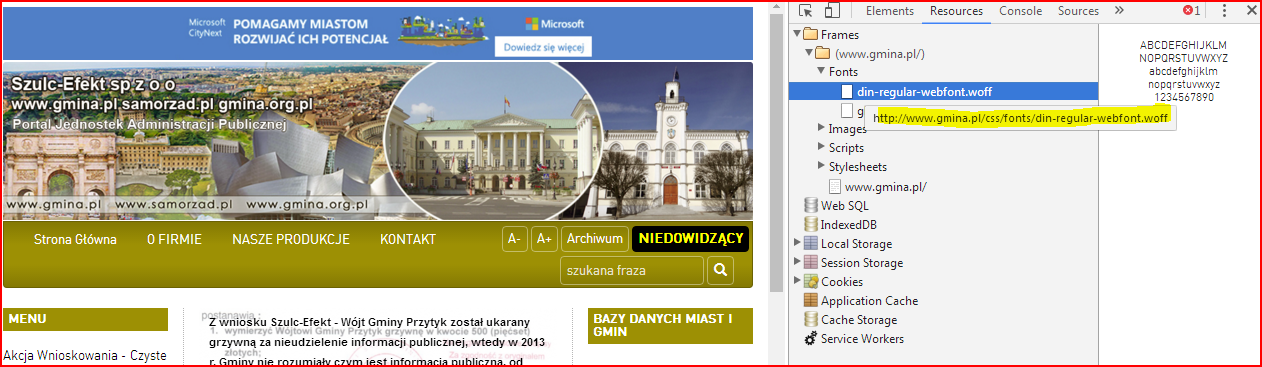
a dokładnie widać, że mówimy tu o:
Font FF DIN jest fontem bardzo czytelnym w małych wielkościach (w małych stopniach pisma) i dlatego jest fontem popularnym w zastosowaniach internetowych - co nie znaczy, że można go nielegalnie używać bez uiszczania odpowiedniej opłaty.
Zapisy o użyciu fontu widnieją w kodzie strony www.gmina.pl:
Font został samodzielnie przekonwertowany z formatu DTP na formaty: woff, ttf, eot,... a takie działanie jest dodatkowo wyraźnie zabronione w licencji.
W pobranych ze strony www.gmina.pl plikach fontów odnajdujemy nieusunięte zapisy copyright producenta:
Powyższy zapis licencyjny potwierdzony jest na stronie producenta:
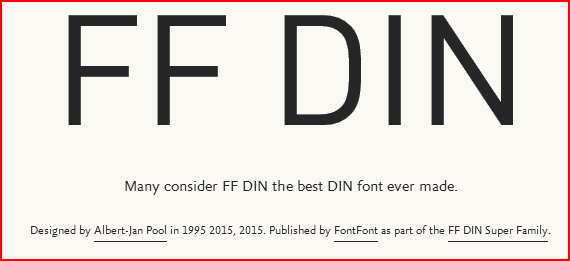
Czy jest to ten sam produkt? - zobaczmy poniżej...
Na obrazku poniżej, prezentujemy nałożone wybrane litery z fontu pobranego ze strony, na te same znaki fontu pochodzącego z obecnej dystrybucji producenta.
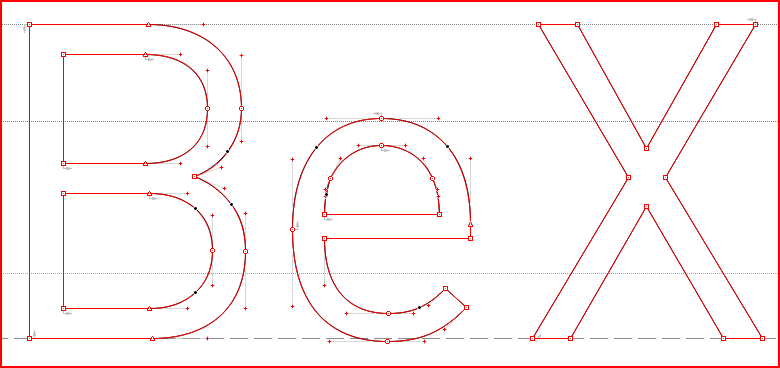
Zapewne zgodność „punkt w punkt” nie powstała przypadkowo...
Oczywiście kopie obu fontów możemy udostępnić odpowiedniemu biegłemu sądowemu, jeśli dostaniemy takie zapytanie.
Dokumentacja dowodowa dla organów sądowych jest właściwie zabezpieczona z zachowaniem najwyższej staranności (kopie stron WWW, pliki CSS, kopie fontów, logi z serwerów, wersje archiwalne stron) i można stwierdzić, że w niedługim czasie Gminy zostaną uwolnione od ew. zarzutu nielegalnego użytkowania fontów FF DIN po niezbędnym zakupie i zrealizowaniu kar przez firmę Szulc Efekt Sp. z o.o. przy wzajemnej współpracy Gmin.
Jakiekolwiek działanie mające na celu podmianę lub usunięcie fontów na stronach GMIN (tzw. dowodów rzeczowych) może tylko prowadzić do eskalacji ew. żądań Producenta i może zostać uznane za próbę mataczenia.